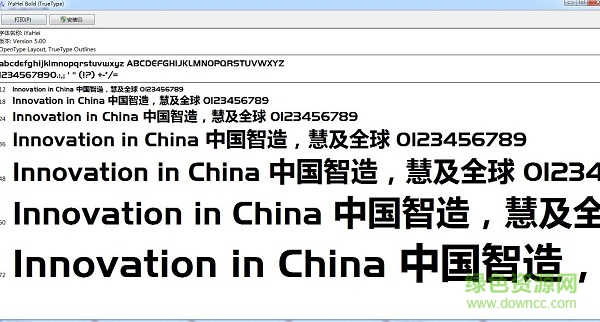
iyahei bold字體
iyahei是什么字體?iyahei字體是一款微軟灰度雅黑字體,包括regular普通版和bold加粗版兩款,比雅黑字體要扁平一些,適合用于linux操作系統(tǒng),歡迎大家免費(fèi)下載!
iyahei字體特點(diǎn)
一種平滑顯示的優(yōu)美黑體,在系統(tǒng)界面和網(wǎng)頁上都可以完美顯示,它的字形略呈扁方而飽滿,筆畫簡(jiǎn)潔而舒展,易于閱讀。
iyahei bold字體